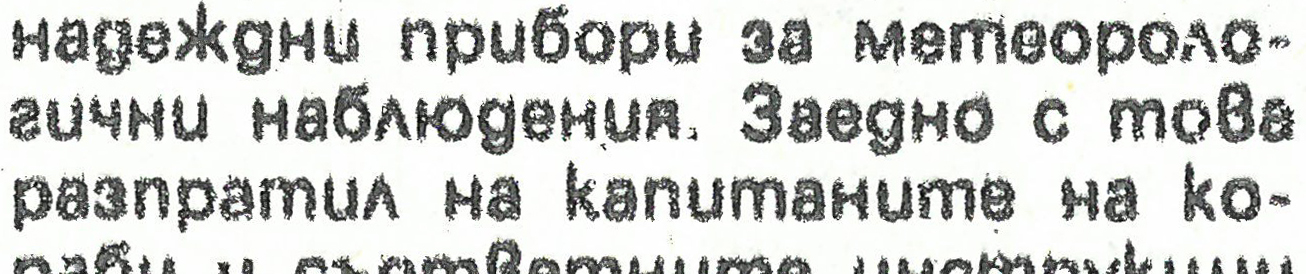
Търся шрифт подобен на този
Оказа се страшно трудно да се намери шрифт на кирилица (стандартен и то), при който буквата "Т" да е като "Ш" наобратно, а "в" да е високо.
Шрифт, най-обикновен, полуръкописен, на който са написани сигурно над 20% от списанията.
Имам предвид втория отгоре надолу. Ще3 съм много благодарен ако ми го намерите или подобен на него.
UnvCyr се оказа шрифта. Самото му име даже е универсално. Ама го няма по сайтовете с шрифтовете.
Не е чак толкова "универсален",колкото го възхваляваш,не е нещо специално! Пробвах го и на мен лично не ми хареса! ;)
Има много по - хубави от него! ;)